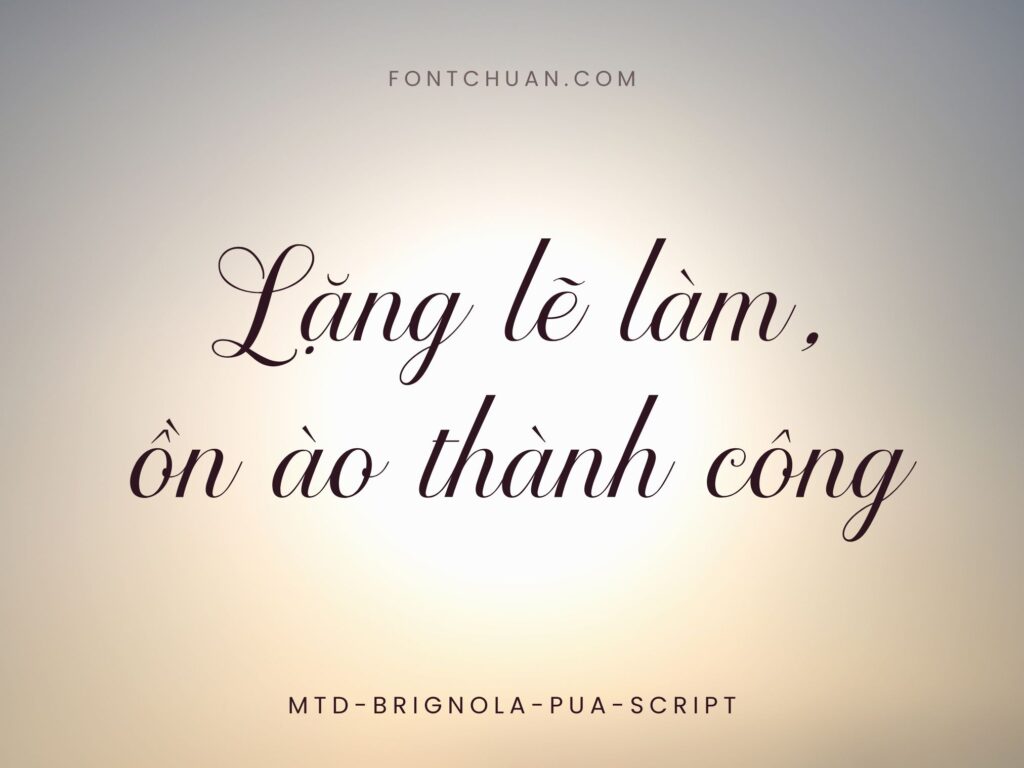
Font MTD Brignola Pua Script Việt Hóa
Brignola PUA Script là một font chữ tinh tế mang phong cách viết tay hiện đại, nổi bật với các đường nét mềm mại và sang trọng. Thiết kế của font này mang đến sự thanh lịch và chuyên nghiệp, giúp tăng tính thẩm mỹ cho các dự án sáng tạo. Để hỗ trợ cộng đồng thiết kế Việt Nam, Mộc Hạ đã Việt hóa font Brignola PUA Script, giúp font này hỗ trợ đầy đủ tiếng Việt cùng hơn 200 ngôn ngữ khác. Phiên bản Brignola PUA Script Việt hóa đã được thành viên Font Chuẩn sưu tầm và đăng tải, nhằm mang đến sự lựa chọn phong phú hơn cho các nhà thiết kế.
Về đặc điểm thiết kế, Brignola PUA Script sở hữu những ký tự có độ uốn lượn nhẹ nhàng, tạo sự liên kết tự nhiên giữa các chữ cái, giúp mang lại cảm giác mềm mại nhưng vẫn đảm bảo tính dễ đọc. Font này rất phù hợp với các thiết kế mang phong cách nghệ thuật, thiệp cưới, thương hiệu thời trang và typography sáng tạo. Ngoài ra, Brignola PUA Script cũng là một lựa chọn lý tưởng cho các ngành nghề như quảng cáo, giáo dục và ẩm thực, mang đến phong cách tinh tế và chuyên nghiệp. Font này cũng rất thích hợp để sử dụng trong các sự kiện như Valentine, Sinh nhật và các dịp lễ hội.